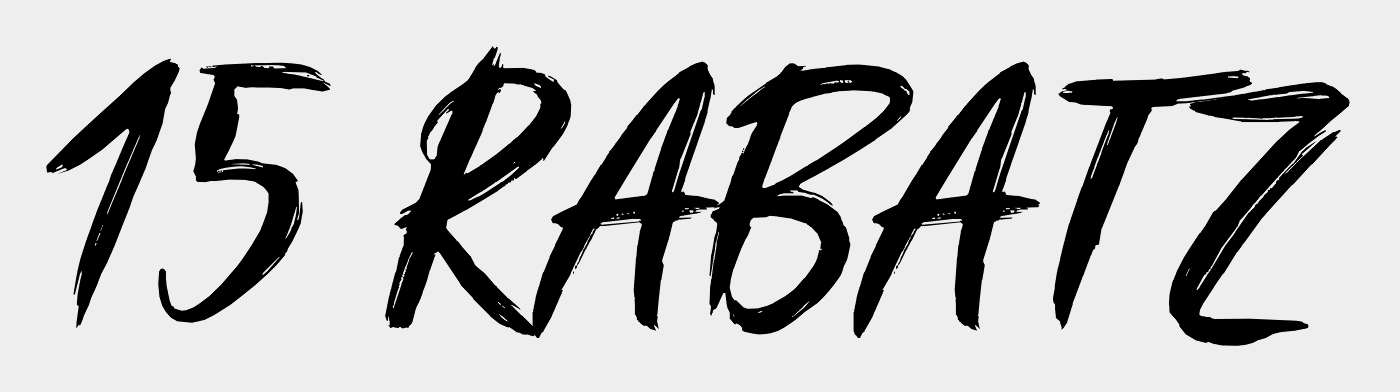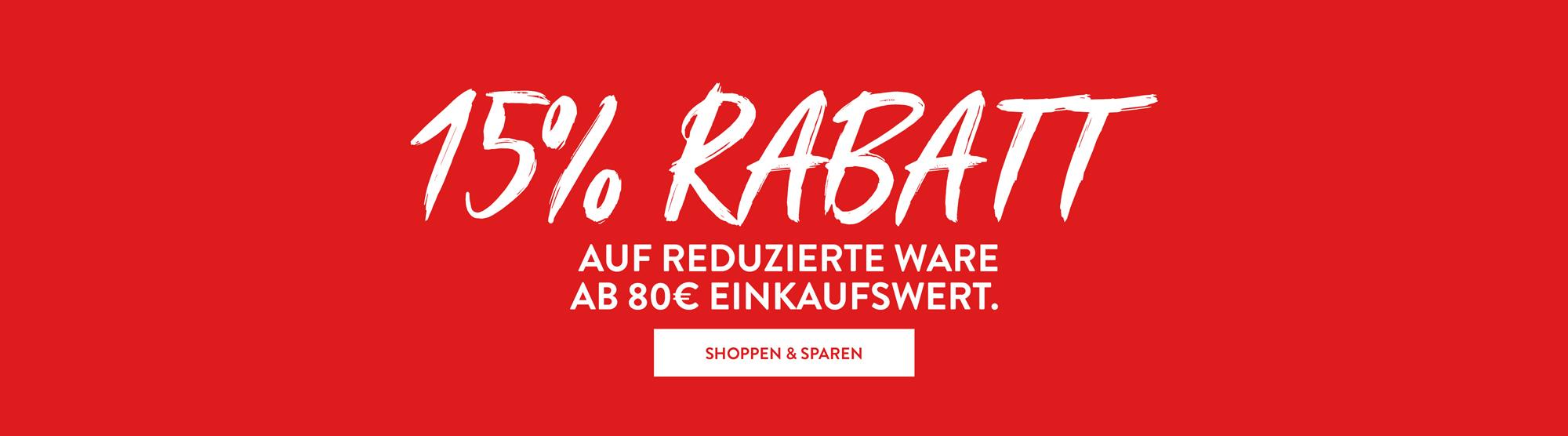
Suche die Hausschrift von Adler Modemärkte
ich suche dringend die Hausschriften von der Modekette Adler!
Einmal diese "Handschrift/Schreibschrift" & die normale darunter.
Wenn möglich eine sehr ähnliche kostenlose Variante.
Die Pinselschrift ist "Blooms Regular".